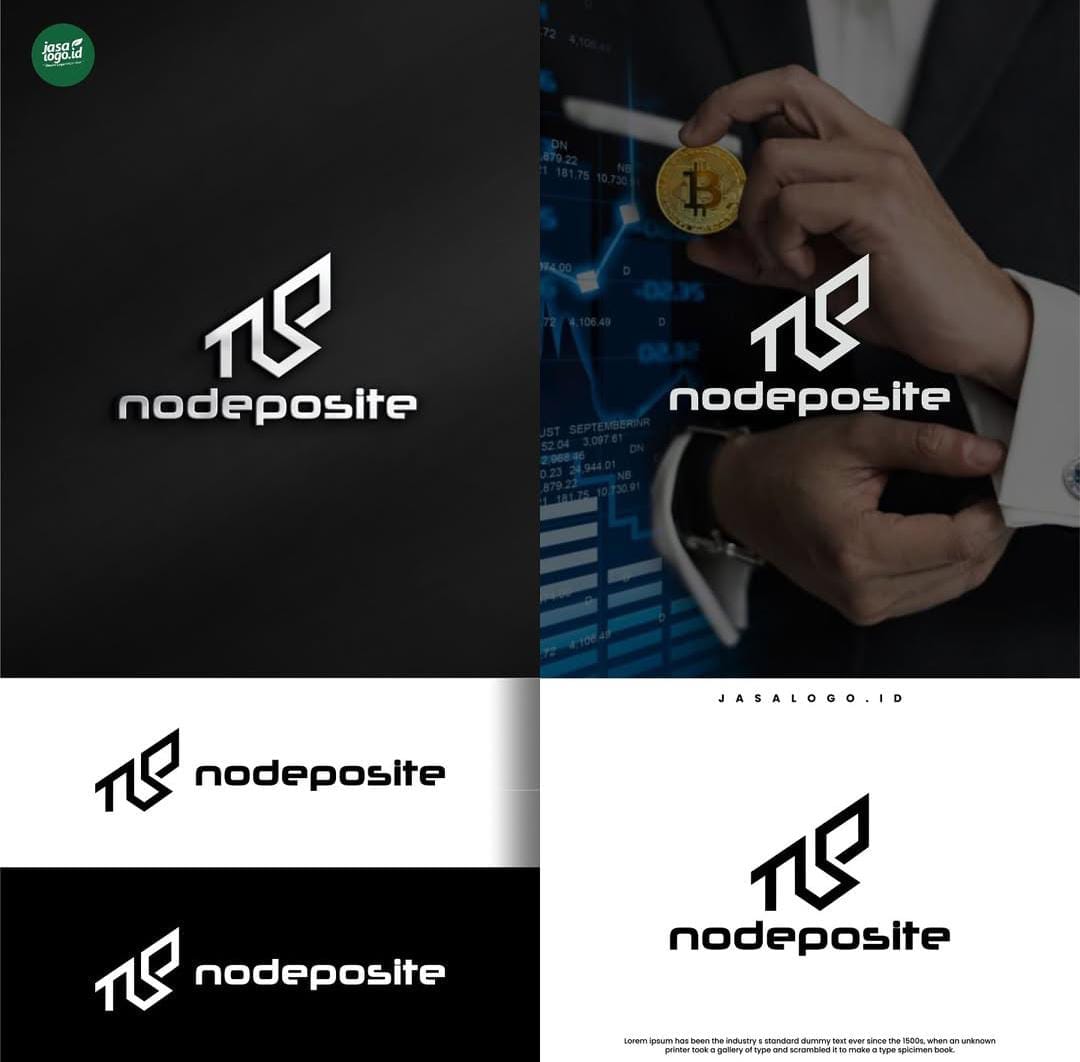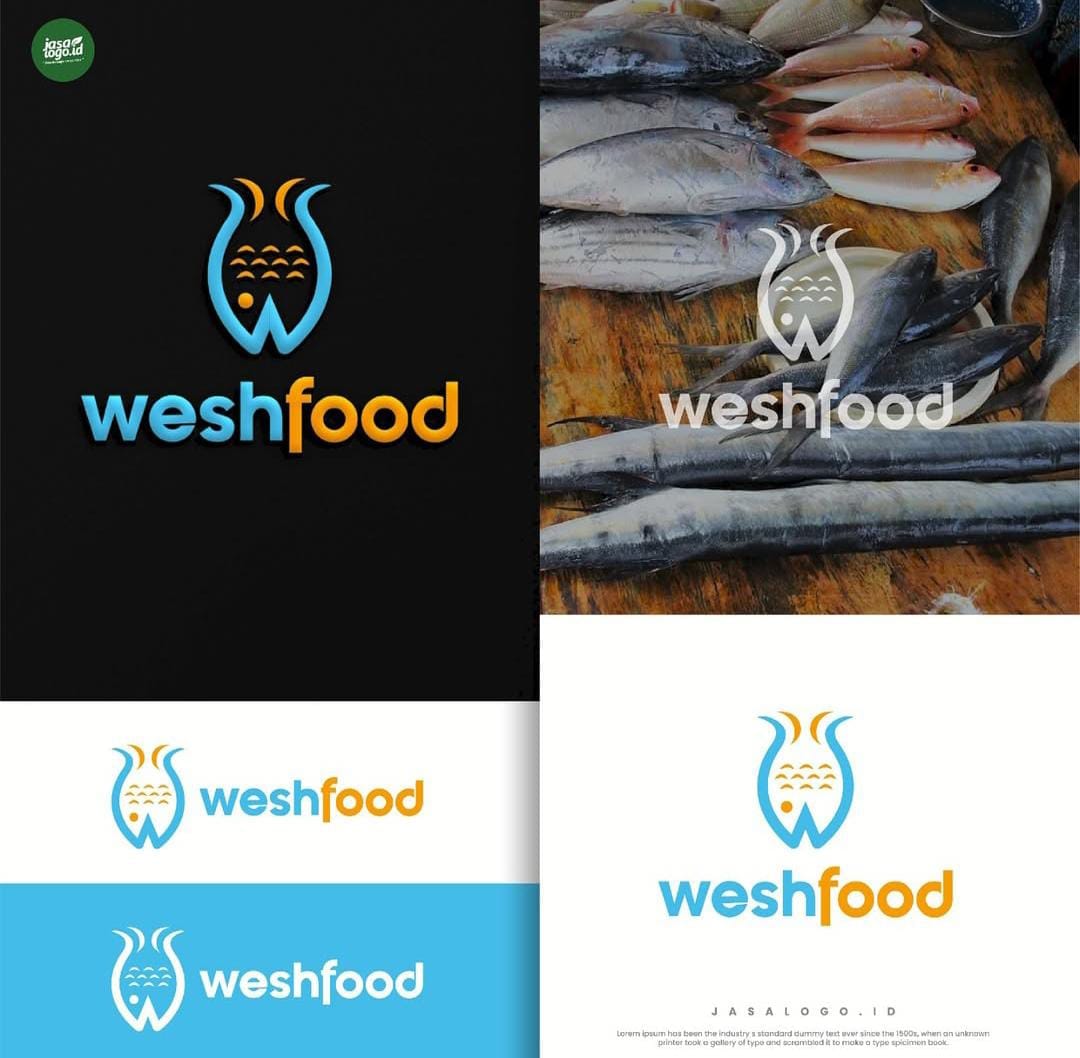
7 Desain Logo dengan Font Lowercase yang Menarik
Tipografi logo bisa memiliki huruf kecil maupun huruf kapital menyesuaikan karakter brand yang ingin diciptakan. Gaya huruf kecil bisa digunakan dalam desain logo untuk tampil ramah dan santai. Desain logo dengan font lowercase akan memiliki desain yang sederhana, cocok untuk brand yang santai.
GAYA HURUF KECIL
Style huruf kecil memungkinkan untuk teks memiliki huruf kecil semua tanpa huruf kapital bahkan pada huruf pertama. Huruf lowercase biasanya menjadi salah satu pilihan dalam memvariasikan gaya tipografi dalam desain atau teks.
Namun perlu diperhatikan jika tidak semua jenis font memiliki variasi style huruf kecil, terkadang beberapa font hanya memiliki huruf kapital. Gaya huruf kecil akan memastikan huruf dalam tipografi memiliki ketinggian yang sama.
7 DESAIN LOGO FONT LOWERCASE
Gaya huruf kecil akan menciptakan tipografi yang berkesan santai, ramah dan bersahabat. Font dengan style huruf lowercase pada desain logo sebaiknya menggunakan jenis font sederhana. Semua huruf dalam teks akan memiliki huruf kecil, termasuk huruf pertama sehingga tipografi tidak berkesan tegas.
Brand Sport Logo Svara
Penggunaan font dengan style huruf lowercase dalam desain logo banyak digunakan pada jenis logo yang hanya menggunakan tipografi saja. Hal ini bertujuan untuk membuat desain logo tampak lebih menarik karena menggunakan huruf kecil bukan kapital. Pada brand sport tersebut, gaya huruf kecil sederhana yang digunakan mudah untuk dibaca.
Gaya huruf juga menciptakan logo yang minimalis dan bergaya modern, cocok merepresentasikan brand sport. Pilihan font sans serif geometris akan menciptakan tipografi logo yang unik. Modifikasi sederhana pada tipografi mendukung logo sederhana tampil lebih menarik.
Brand Anak-anak Logo Little Mima
Pada brand anak-anak penggunaan font lowercase populer untuk menciptakan desain logo sederhana dan bergaya ramah. Kesan ramah dan bersahabat yang diciptakan cocok untuk menarik perhatian anak-anak. Pemilihan font huruf kecil disesuaikan dengan target konsumen anak-anak.
Huruf kecil juga lebih mudah dibaca dan tidak berkesan serius sehingga bisa disukai anak-anak. Font sans serif yang tipis dan bersih akan menciptakan kesan ramah, terutama dengan gaya huruf kecil.
Brand Coffee Logo Ara Coffee
Logo coffee tersebut juga menggunakan gaya huruf kecil untuk menciptakan nama brand yang mudah diingat dan berkesan ramah. Brand coffee sangat cocok dengan style font yang ramah karena merepresentasikan brand yang mudah didekati.
Desain logo coffee ara tersebut menggunakan style huruf kecil yang dikombinasikan dengan huruf kapital, tetapi memiliki ukuran huruf yang sama. Gaya tipografi ini menciptakan desain logo tampak lebih unik dan menarik. Pada desain logo coffee, gaya huruf lowercase akan merepresentasikan brand yang estetik, santai dan ramah.
Brand Makanan Logo Weshfood
Huruf lowercase yang bisa merepresentasikan brand yang ramah dan bersahabat membuatnya cocok juga untuk brand makanan. Salah satu penggunaan gaya huruf kecil pada logo makanan karena menciptakan brand yang berkesan lebih ramah. Terutama jika menggunakan gaya font bulat atau dengan sudut cursive seperti pada logo tersebut.
Font tebal yang digunakan memiliki sudut melengkung sehingga menciptakan kesan ramah yang didukung huruf kecil. Gaga huruf kecil tersebut efektif menciptakan brand makanan yang berkesan ramah. Font tersebut juga sederhana sehingga menciptakan desain logo sederhana.
Brand Teknologi atau Finance Logo Nodeposite
Gaya huruf kecil sering dipilih untuk merepresentasikan brand yang santai dan bersahabat, tetapi juga bisa tampil modern dan geometris. Logo untuk brand finance tech tersebut menggunakan jenis font geometris yang sederhana. Font geometris menggunakan gaya huruf lowercase sehingga desain logo tidak berkesan terlalu kaku dan tegas.
Gaya huruf kecil pada tipografi geometris bisa menciptakan desain logo yang lebih santai dan bersahabat. Desain logo terlihat tidak begitu kaku dan tajam, teks juga mudah dibaca karena tampil sederhana. Bentuk geometris menciptakan tipografi yang unik dan merepresentasikan identitas brand dengan baik.
Brand Fashion Logo Bikinkeativ
Desain logo untuk brand fashion tersebut menggunakan font sederhana dengan gaya huruf lowercase. Gaya huruf yang tipis membuat desain logo tampak ramah, santai dan bersahabat. Desain logo juga tampak lebih elegan dan merepresentasikan brand fashion yang terpercaya.
Desain logo tak hanya sering menggunakan font huruf kapital tetapi juga bisa menggunakan huruf lowercase. Gaya huruf kecil akan menciptakan desain brand yang santai, ramah dan bersahabat. Biasanya sering digunakan pada jenis brand makanan, minuman, fashion, coffee hingga brand anak-anak. Tujuannya agar brand tampil ramah dan mudah untuk didekati.